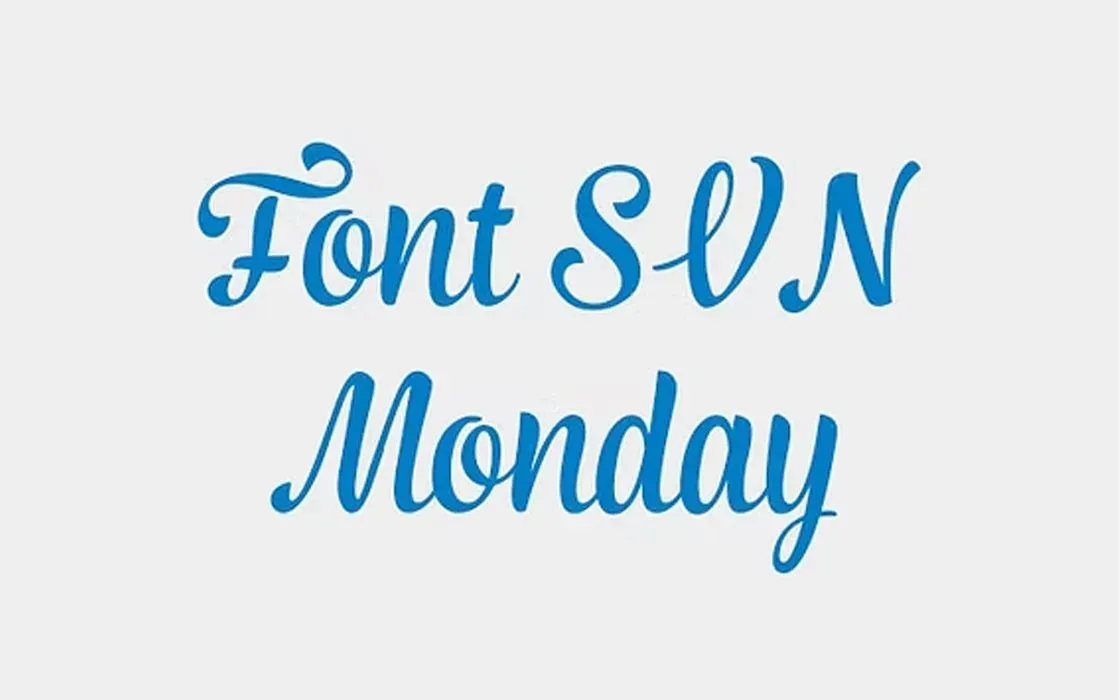
SVN Monday là một font chữ viết tay (handwritten script) mang phong cách tự nhiên, mềm mại và bay bổng, như những nét chữ được viết bằng tay trên giấy với sự chăm chút nhẹ nhàng nhưng không gò bó. Các ký tự có nét cong uyển chuyển, độ nghiêng nhẹ và kết nối mượt mà, tạo cảm giác thân thiện, gần gũi và đầy cảm xúc.
Font phù hợp với các thiết kế mang hơi thở cá nhân, nhẹ nhàng hoặc nữ tính, chẳng hạn như: thiệp mời, bìa sách, logo thương hiệu thời trang – mỹ phẩm, blog cá nhân, hay các sản phẩm sáng tạo như bullet journal, hand-lettering, bao bì thủ công.
Font gốc Monday Script do nhà thiết kế độc lập sáng tạo (tên chưa công bố rộng rãi), với mục tiêu mang lại một kiểu chữ viết tay dễ sử dụng, vừa đời thường vừa duyên dáng. Đặc điểm nổi bật là các nét nối linh hoạt và độ cao thấp bất quy tắc giữa các chữ cái, giúp tạo cảm giác như được viết hoàn toàn bằng tay thật.